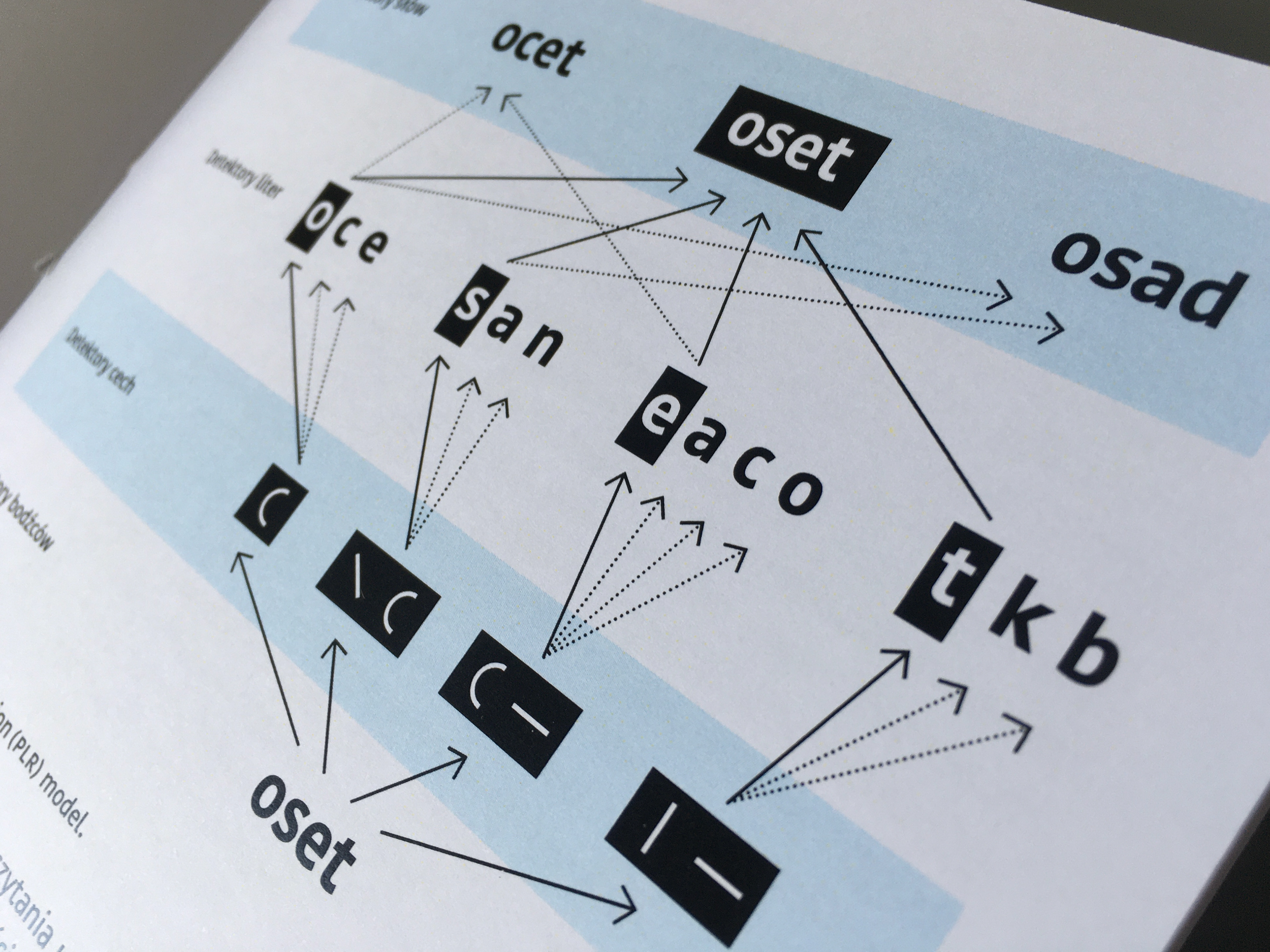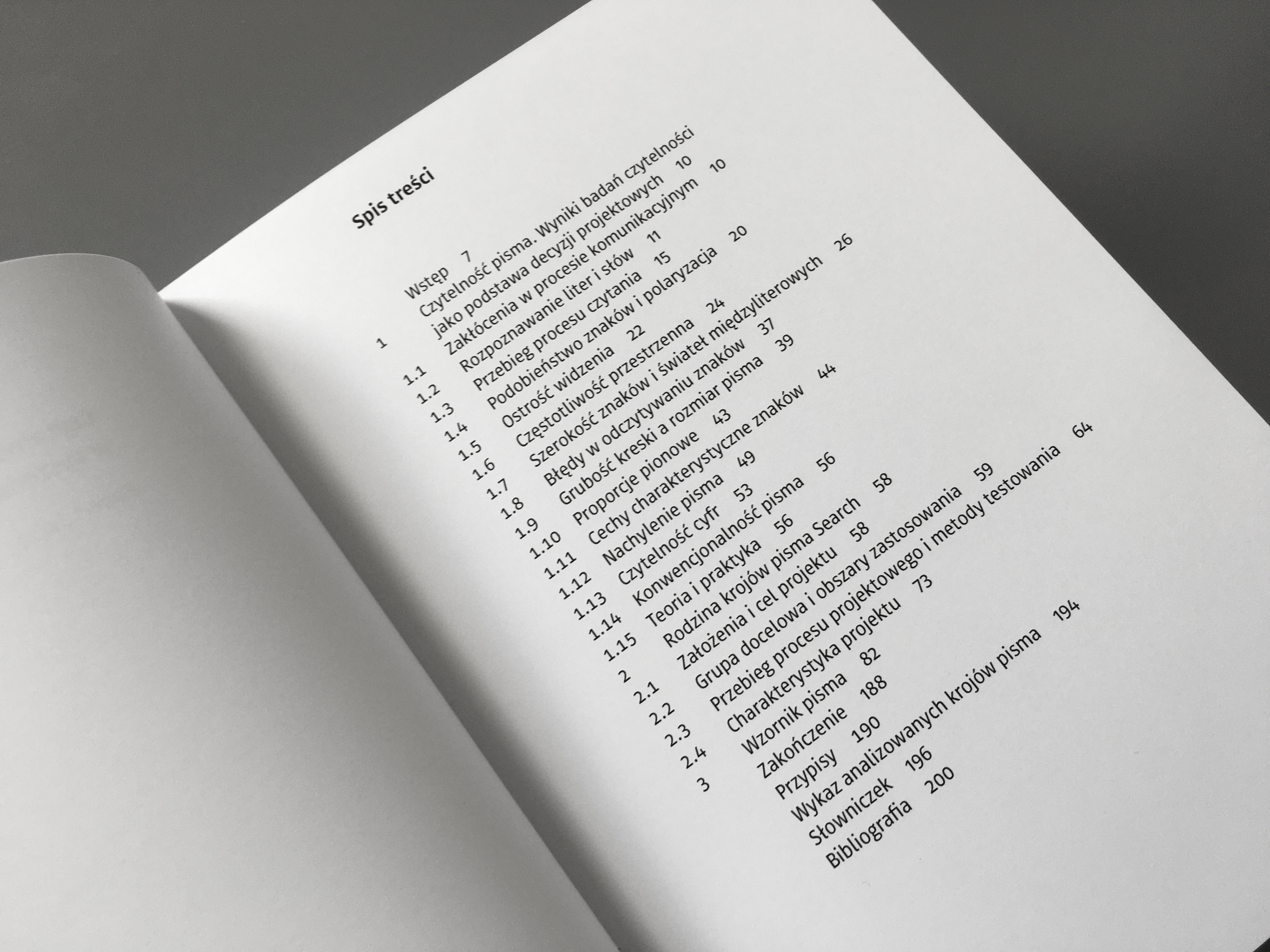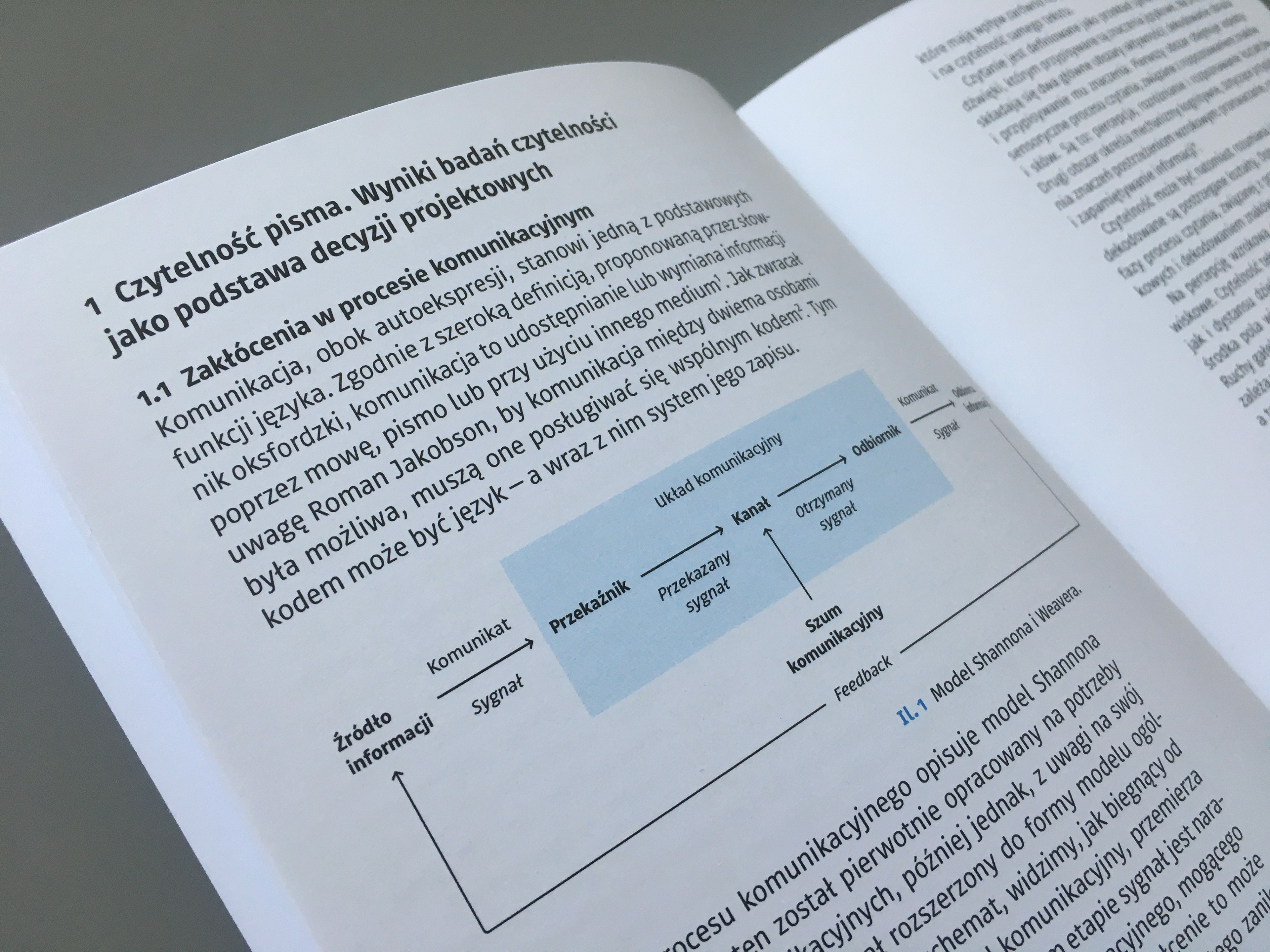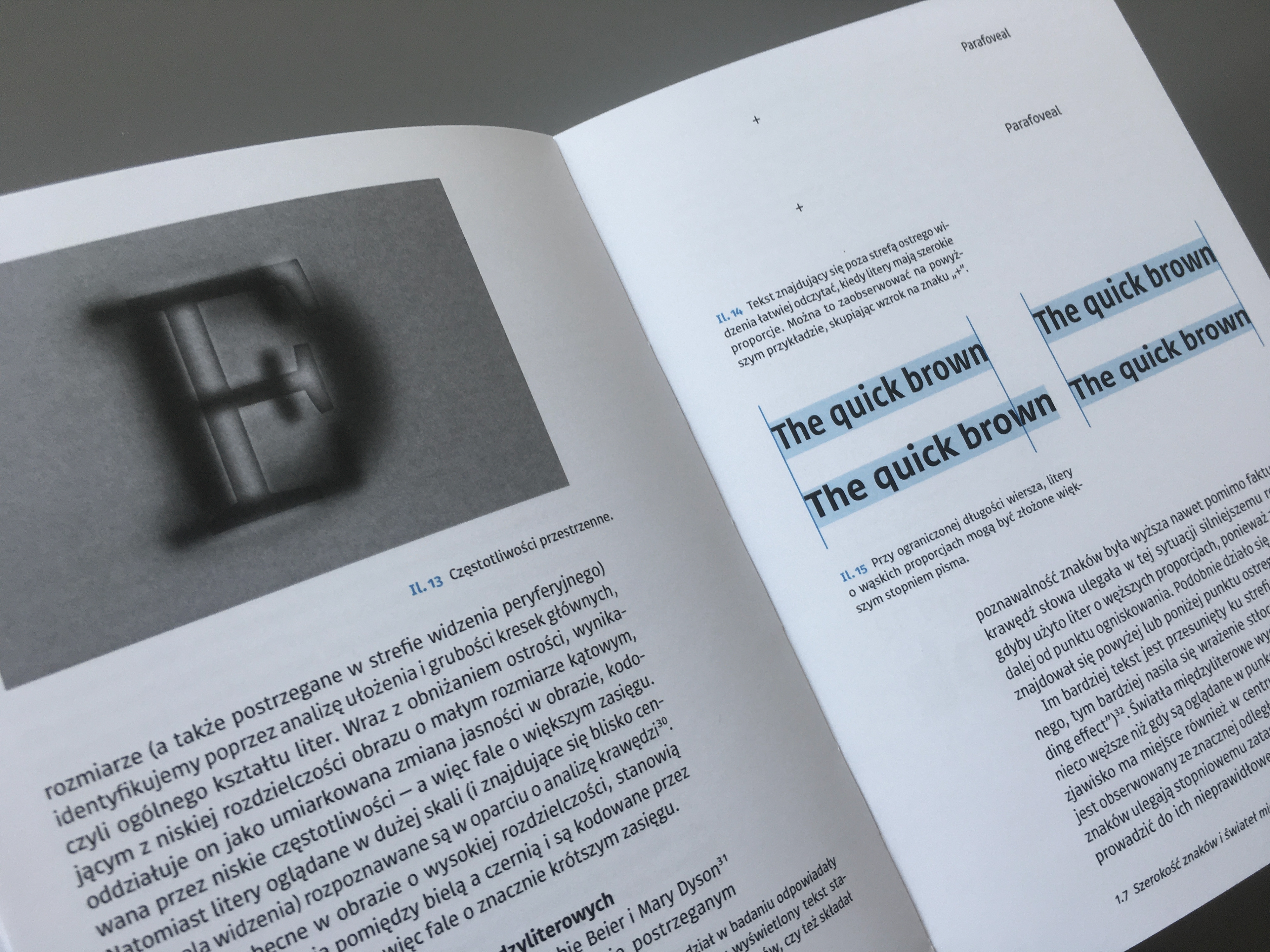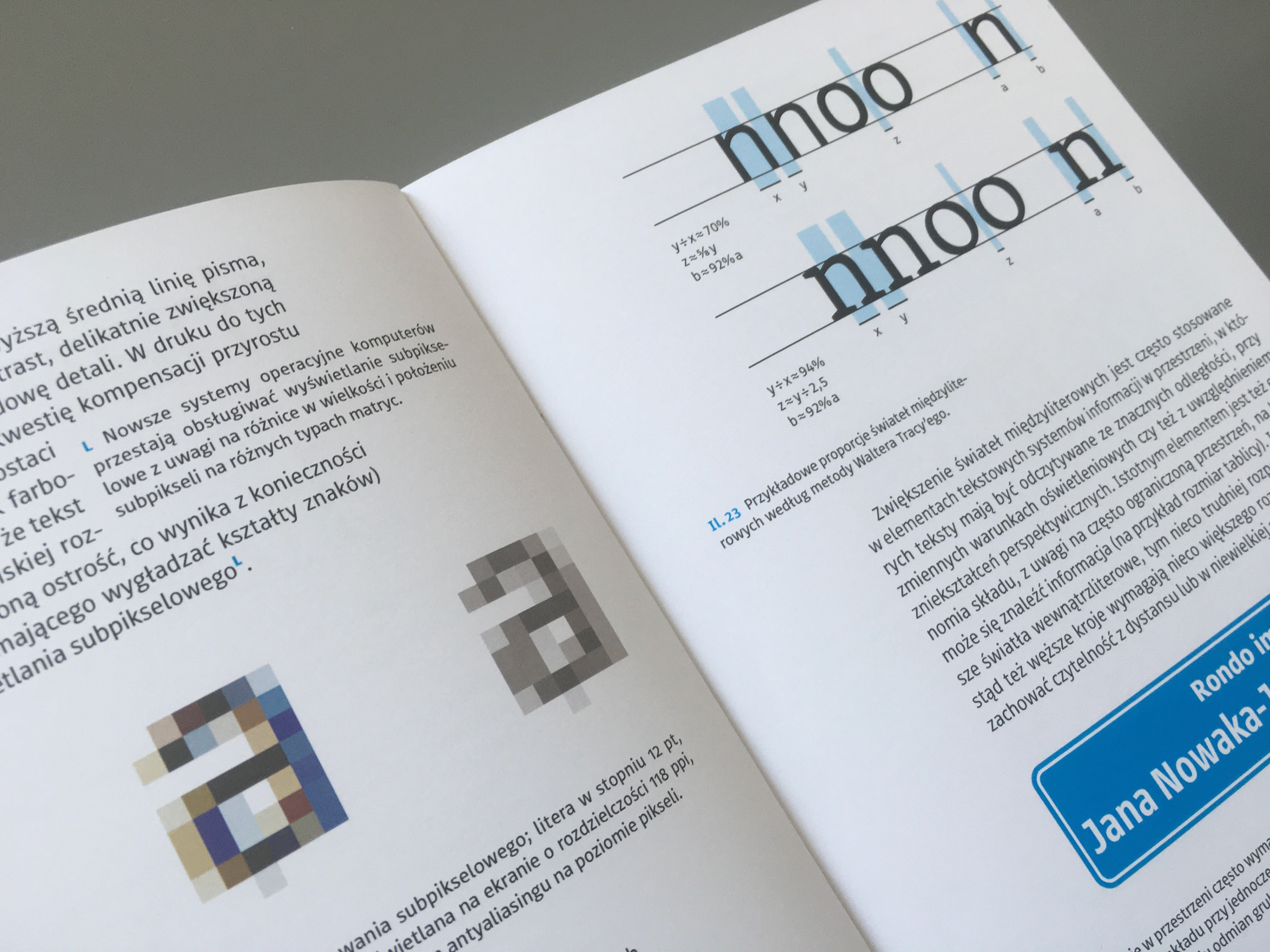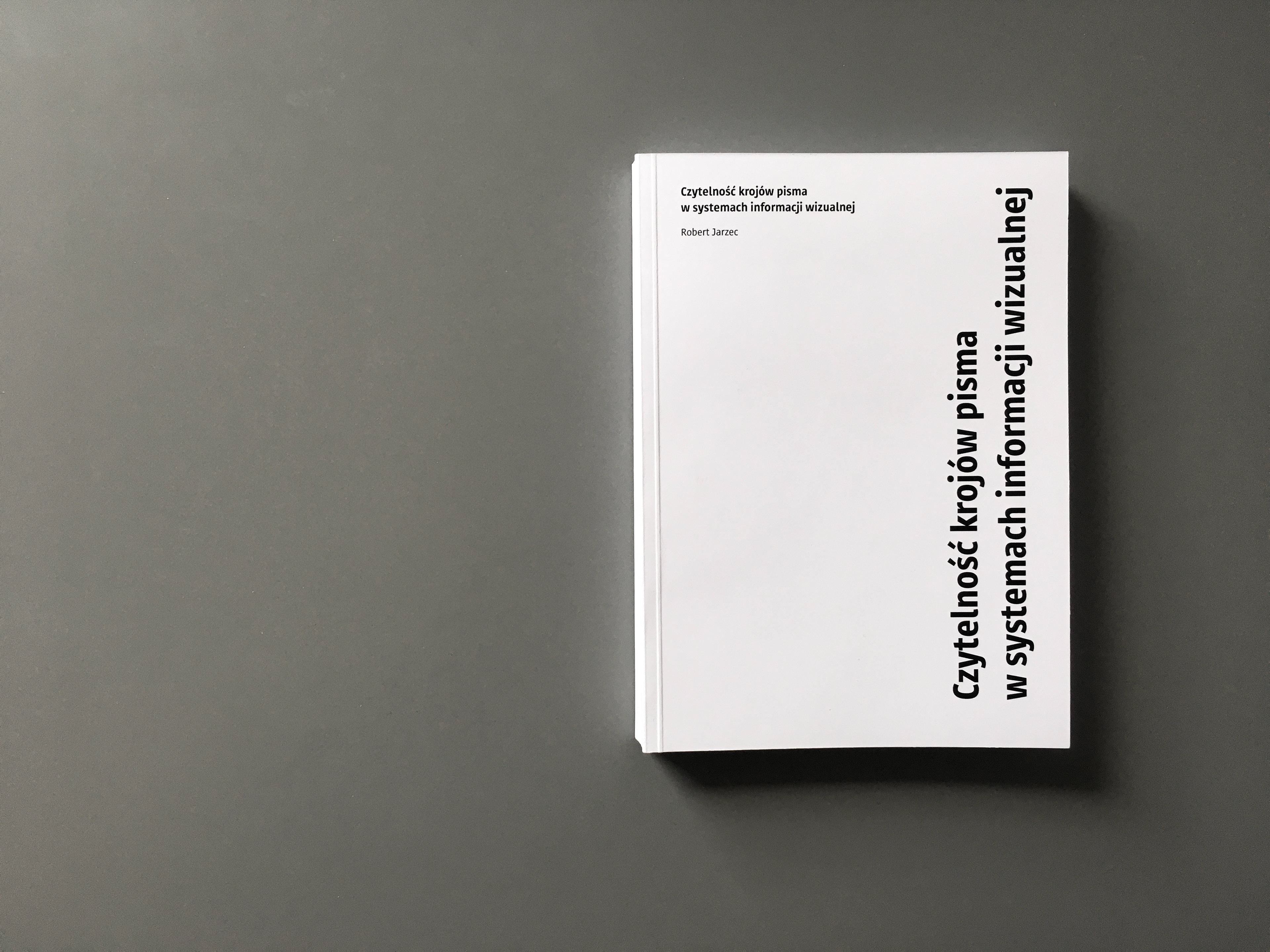
Wyniki badań naukowych dostarczają szeregu informacji, które mogą pomóc w zapewnieniu odpowiednio wysokiej czytelności tekstu w różnorodnych warunkach lektury. Jednocześnie czytelność pozostaje w znacznej mierze parametrem subiektywnym.
Niniejszy projekt stanowi przegląd wyników współczesnych badań czytelności pisma. Omówione informacje zostają zestawione z obserwacjami i doświadczeniami projektantów pisma i typografów.
Komunikacja, obok autoekspresji, stanowi jedną z podstawowych funkcji języka. Zgodnie z szeroką definicją, proponowaną przez słownik oksfordzki, komunikacja to udostępnianie lub wymiana informacji poprzez mowę, pismo lub przy użyciu innego medium. Jak zwracał uwagę Roman Jakobson, by komunikacja między dwiema osobami była możliwa, muszą one posługiwać się wspólnym kodem. Tym kodem może być język – a wraz z nim system jego zapisu.
Przebieg procesu komunikacyjnego opisuje model Shannona i Weavera. Model ten został pierwotnie opracowany na potrzeby technologii telekomunikacyjnych, później jednak, z uwagi na swój uniwersalny charakter, został rozszerzony do formy modelu ogólnego. Śledząc nakreślony w nim schemat, widzimy, jak biegnący od nadajnika sygnał, wchodząc w układ komunikacyjny, przemierza kanał łączący przekaźnik i odbiornik. Na tym etapie sygnał jest narażony na działanie tak zwanego szumu komunikacyjnego, mogącego powodować zniekształcenie informacji. Zniekształcenie to może prowadzić do wypaczenia treści, obniżenia lub całkowitego zaniku czytelności komunikatu.
Wystąpienie szumu, zakłócającego odbiór komunikatu wizualnego, może mieć związek zarówno z ograniczeniami widoczności, jak i z obecnością innych niż wzrokowe bodźców sensorycznych, absorbujących uwagę odbiorcy w chwili otrzymania komunikatu.
W wypadku pisma, możliwość odebrania i przyswojenia informacji jest warunkowana przez szereg silnie skorelowanych czynników, które mają wpływ zarówno na przebieg całego procesu czytania, jak i na czytelność samego tekstu.
Czytanie jest definiowane jako przekład symboli wizualnych na dźwięki, którym przypisywane są znaczenia językowe. Na proces ten składają się dwa główne obszary aktywności: dekodowanie obrazu i przypisywanie mu znaczenia. Pierwszy obszar obejmuje aspekty sensoryczne procesu czytania, związane z rozpoznawaniem znaków i słów. Są to: percepcja, rozróżnianie i rozpoznawanie kształtów. Drugi obszar określa mechanizmy kognitywne, dotyczące przypisywania znaczeń postrzeżeniom wzrokowym: przetwarzanie, rozumienie i zapamiętywanie informacji.
Czytelność może być natomiast rozumiana jako łatwość, z jaką dekodowane są postrzegane kształty. Dotyczy ona więc pierwszej fazy procesu czytania, związanej z przetwarzaniem bodźców wzrokowych i dekodowaniem znaków pisma.​​​​​​​
Czytelność (ang. legibility; odróżnialność, rozpoznawalność znaków) – łatwość, z jaką identyfikowane są postrzegane znaki pisma. Dotyczy pierwszej fazy procesu czytania, związanej z przetwarzaniem bodźców wzrokowych i dekodowaniem kształtów.
Łatwość lektury (ang. readability) – poziom wygody, odczuwanej przez czytelnika w trakcie lektury.
Rozpoznawalność znaków ma bezpośrednie przełożenie na łatwość lektury.
Na percepcję wzrokową ogromny wpływ mają warunki środowiskowe. Czytelność tekstu zależy więc zarówno od wielkości liter, jak i dystansu dzielącego je od oka. Położenie tekstu względem środka pola widzenia warunkuje ostrość, z jaką widzimy litery. Ruchy gałek ocznych, częstość występowania i długość fiksacji oka zależą w niemałym stopniu od wielkości tekstu i jego rozświetlenia, a także od długości wiersza i wielkości interlinii. Do tego dochodzi rodzaj i natężenie oświetlenia, kontrasty barwne i wrażliwość oka na różne długości fal świetlnych. Nie bez znaczenia są także użyte media i warunki technicznej reprodukcji – w tym parametry nośników informacji mające wpływ na odbijanie lub emisję światła. W wypadku tekstów czytanych z dystansu, należy też zwrócić uwagę na zniekształcenia perspektywiczne i zaburzenia ostrości wywołane przez inne niż wymienione wyżej czynniki – na przykład warunki atmosferyczne, brak stabilizacji obrazu lub zmienną odległość od obserwatora.
Należy pamiętać, że wszystkie wymienione czynniki silnie na siebie wzajemnie oddziałują i żaden z nich nie powinien być rozpatrywany w oderwaniu od pozostałych. Natomiast znajomość tych mechanizmów oraz ich powiązań może być pomocna w określaniu poziomu czytelności, jaki może cechować dany tekst.
(Fragment rozdziału 1. Czytelność pisma. Wyniki badań czytelności
jako podstawa decyzji projektowych
Książka Czytelność krojów pisma w systemach informacji wizualnej oraz rodzina krojów pisma Site to elementy rozprawy doktorskiej, przygotowanej na Wydziale Grafiki i Komunikacji Wizualnej Uniwersytetu Artystycznego im. Magdaleny Abakanowicz w Poznaniu. Autor: Robert Jarzec. Promotor: prof. dr hab. Krzysztof Kochnowicz. Recenzenci: dr hab. Ewa Satalecka, prof. PJATK, dr hab. Jacek Mrowczyk, prof. ASP w Katowicach.